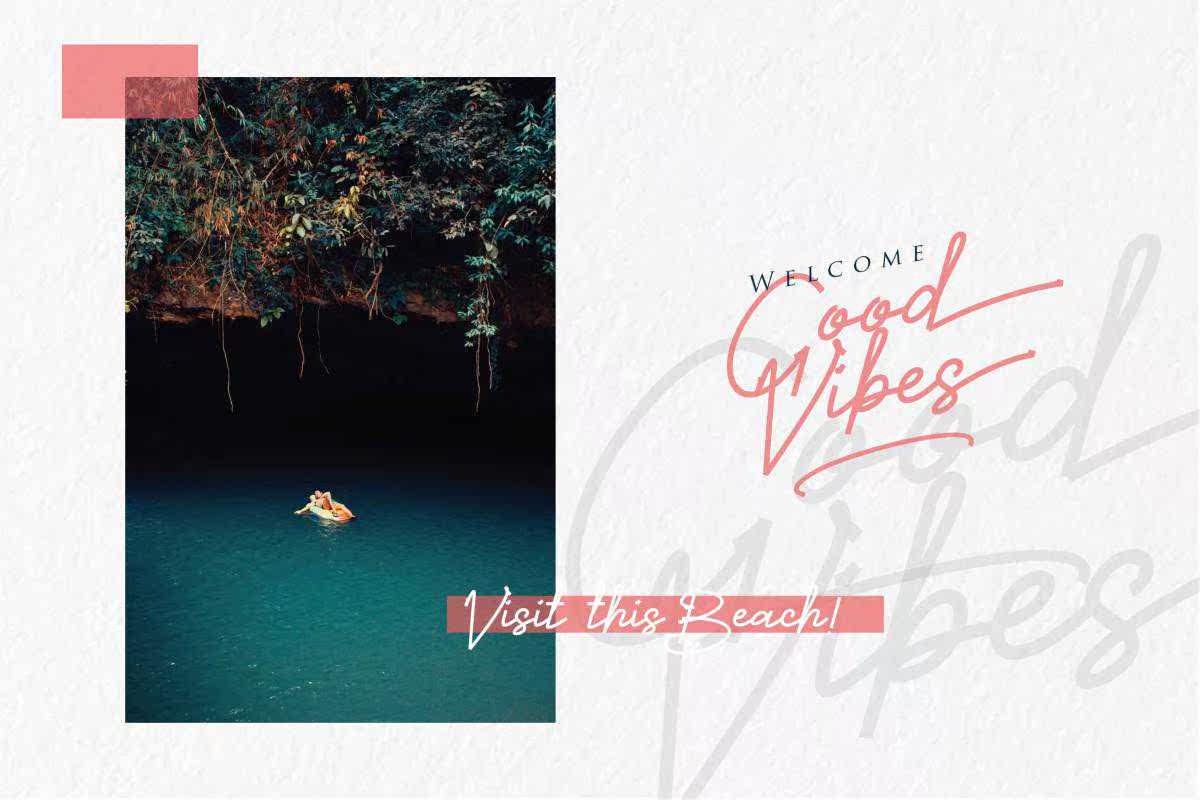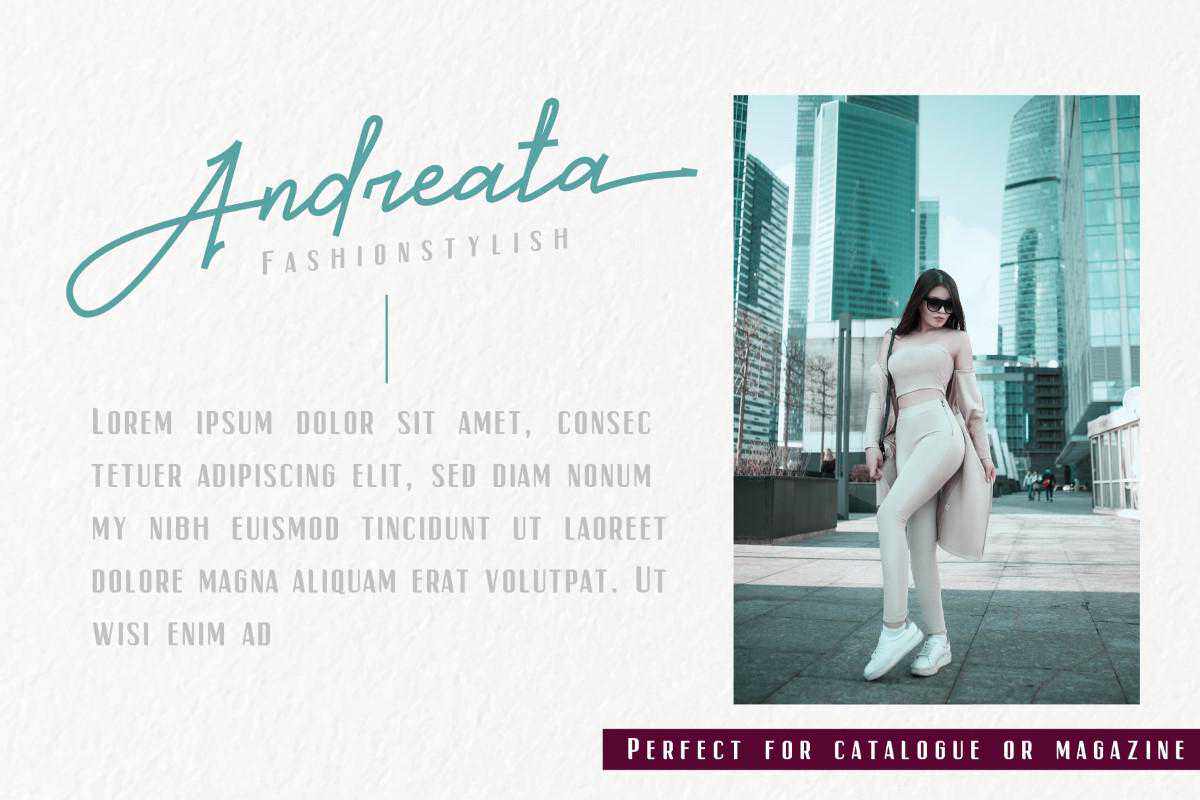
SweetCarissa是一款经典的LoveLysignature FontDuo,简单的Classify FontScription和Sans,具有完美的配对组合,具有多种类型的特征,包括风格的交替、首字母和结尾形式以及描述版本的连字。SweetCarissa是一款经典的LoveLysignatureFontDuo,简单的Classify FontScription和Sans,具有完美的配对组合,具有不同风格、首字母和末字母形式以及描述版本的连字等五种类型特征。